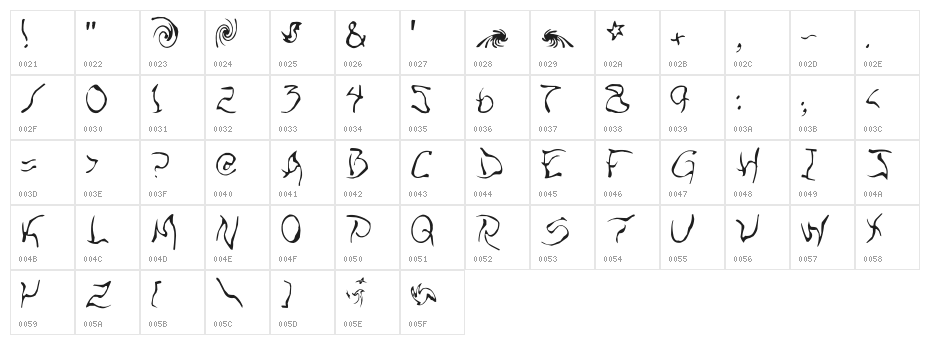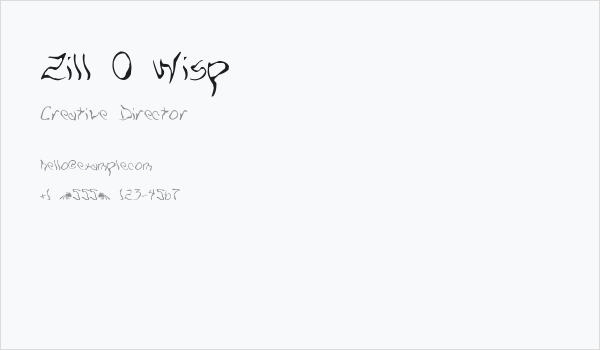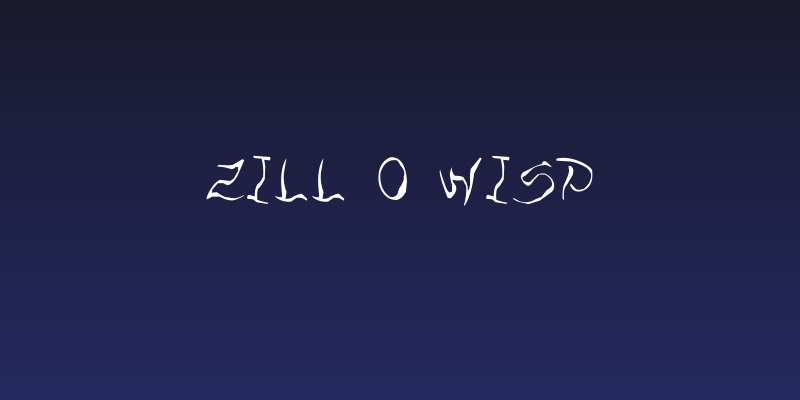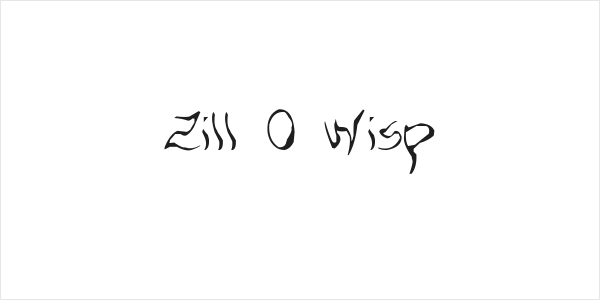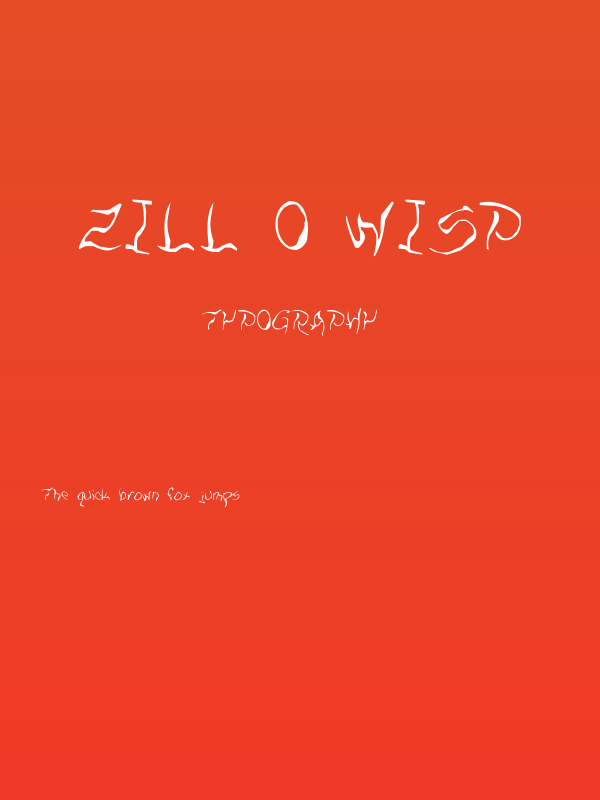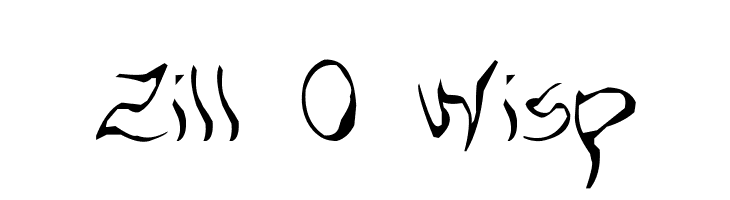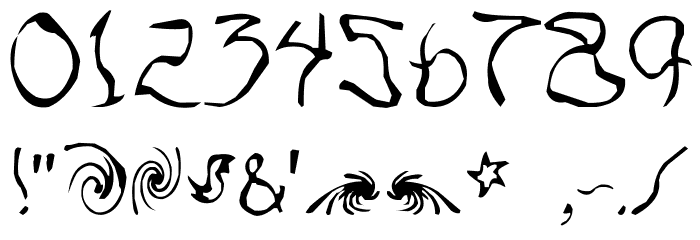
Zill O Wisp Font
ZILL-O-WISP Groß
ZILL-O-WISP Kleinbuchstaben
ZILL-O-WISP Anderer Schreiben
| Anwendungsfall | Headlines, Logos, Artistic projects |
| Vorgeschlagene Projekte | Ideal for fantasy-themed designs, children's book covers, creative posters, and artistic branding. |